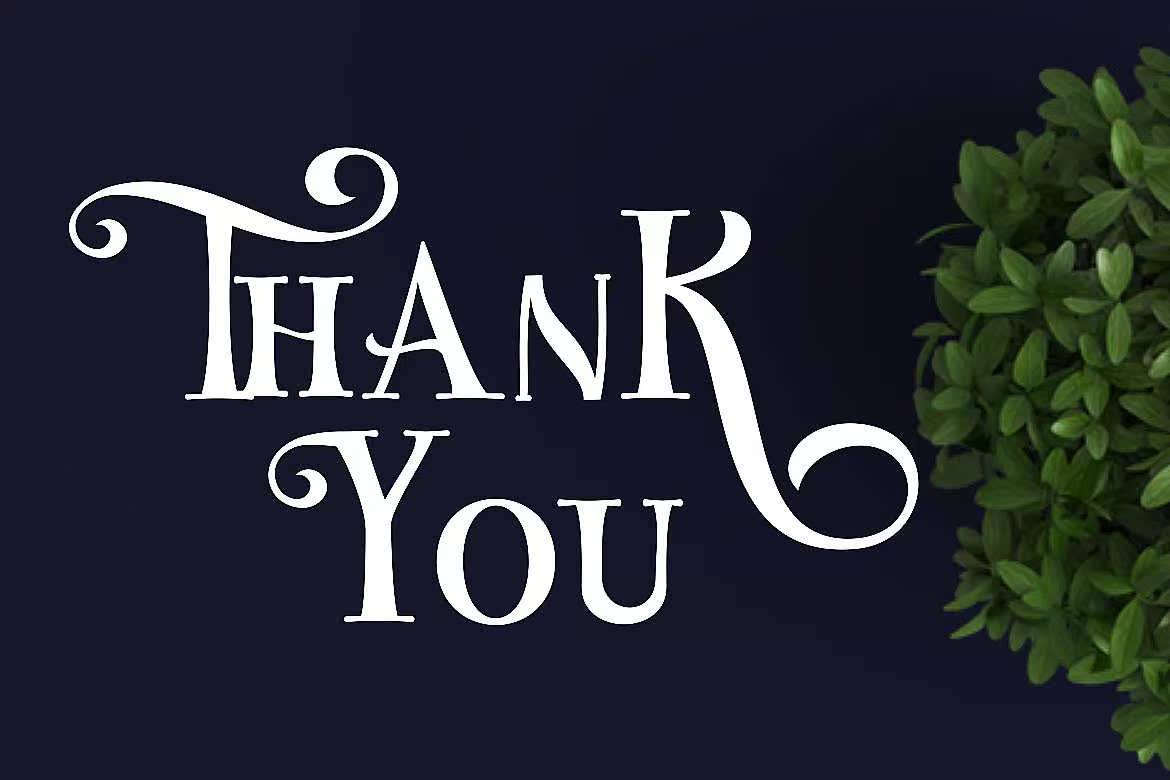
Misteris Fund Display Font具有少许螺纹。此Font具有两种样式,即常规样式和所有大写样式。还可以在某个字符中使用替代样式。Misteris Font非常适合创建徽标、打印模板、海报、品牌、衬衫、礼品、报价或任何其他样式。Misteris Fund DisplayFont具有少许螺纹。此Font具有两种样式,常规和所有大写字母。也可在某些字符中使用替代字符。MisteriFont非常适合创建徽标、打印模板、商标、衬衫、礼品、报价或任何内容